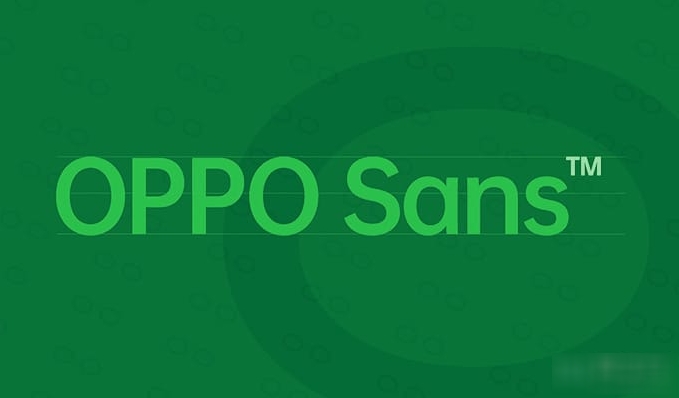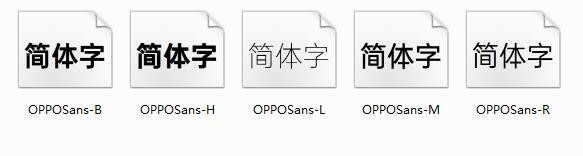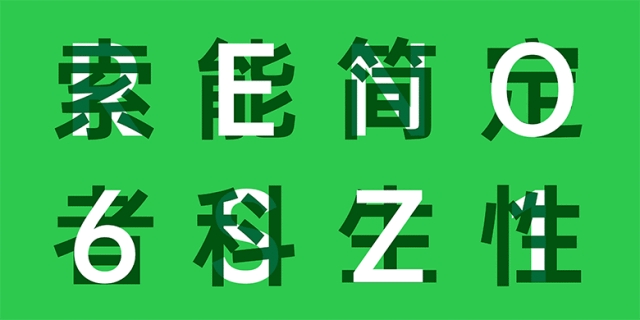
oppo sans字體官方版是oppo品牌字體,可以免費授權(quán)商用,該字體筆畫簡化,看起來自然舒適,線條流暢,簡約時尚,更具現(xiàn)代感和未來感,整體造型挺拔優(yōu)雅,充滿了生命力,適用的領(lǐng)域場合十分廣泛,滿足大家的字體設計需求!
OPPO 全新品牌字體 OPPO Sans 中文部分由漢儀字庫字體設計總監(jiān)朱志偉指導,黃珍元設計完成,西文部分則由美國 Pentagram 五角公司設計,漢儀字庫西文項目組負責人張暄協(xié)作完成。OPPO 品牌字體緊隨品牌升級的步調(diào),從品牌理念出發(fā),用文字全方位探索科技美感,用獨特的語言打造具有標志性的、與眾不同的全新品牌體驗。
-- OPPO Sans 是一套簡潔風格的中文字體,字型設計很有現(xiàn)代感和科技感。
-- 字體采用了全新骨架設計,中宮自然舒適、更加挺拔優(yōu)雅,筆畫獲得了簡化,去除出腳等更多細節(jié)的處理使得字體顯得更加的干凈。
-- 字體簡潔富有變化的線條融入曲線的美學,適合用來作為 IT 數(shù)碼類海報 Banner 等各類作品的設計素材使用,實用性相當廣泛。
OPPO Sans字體中文版根據(jù)粗細程度劃分出了5種系列,分別為:Light / Regular / Medium / Bold / Heavy ,可適用于不同設計與閱讀需求。這五種字重分別為:
OPPO Sans 字體定位為全球化品牌字體,包含中文和西文共 226003 個字符,共覆蓋 21 個國家語言,共 11 個語種,字型非常的豐富。